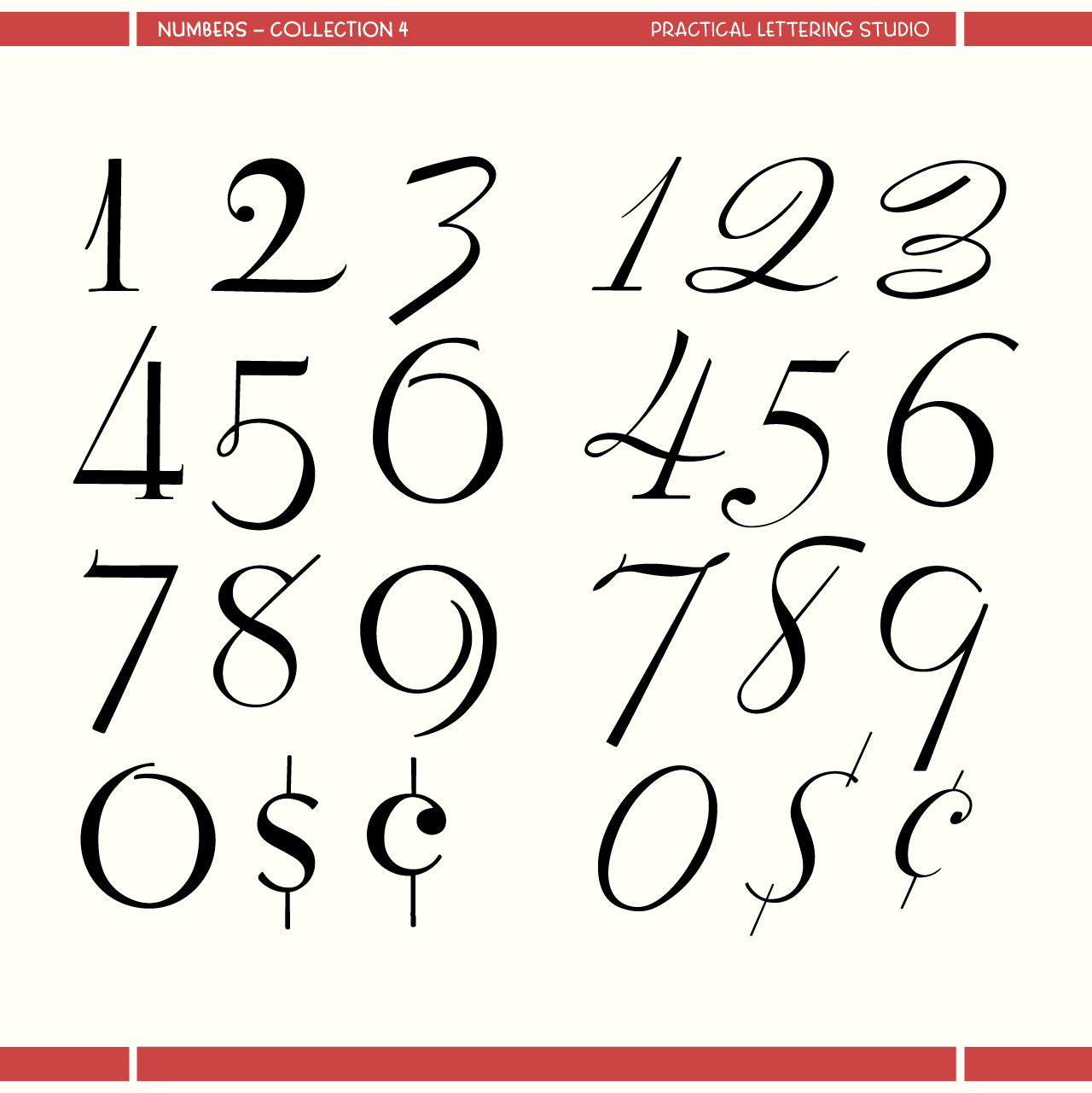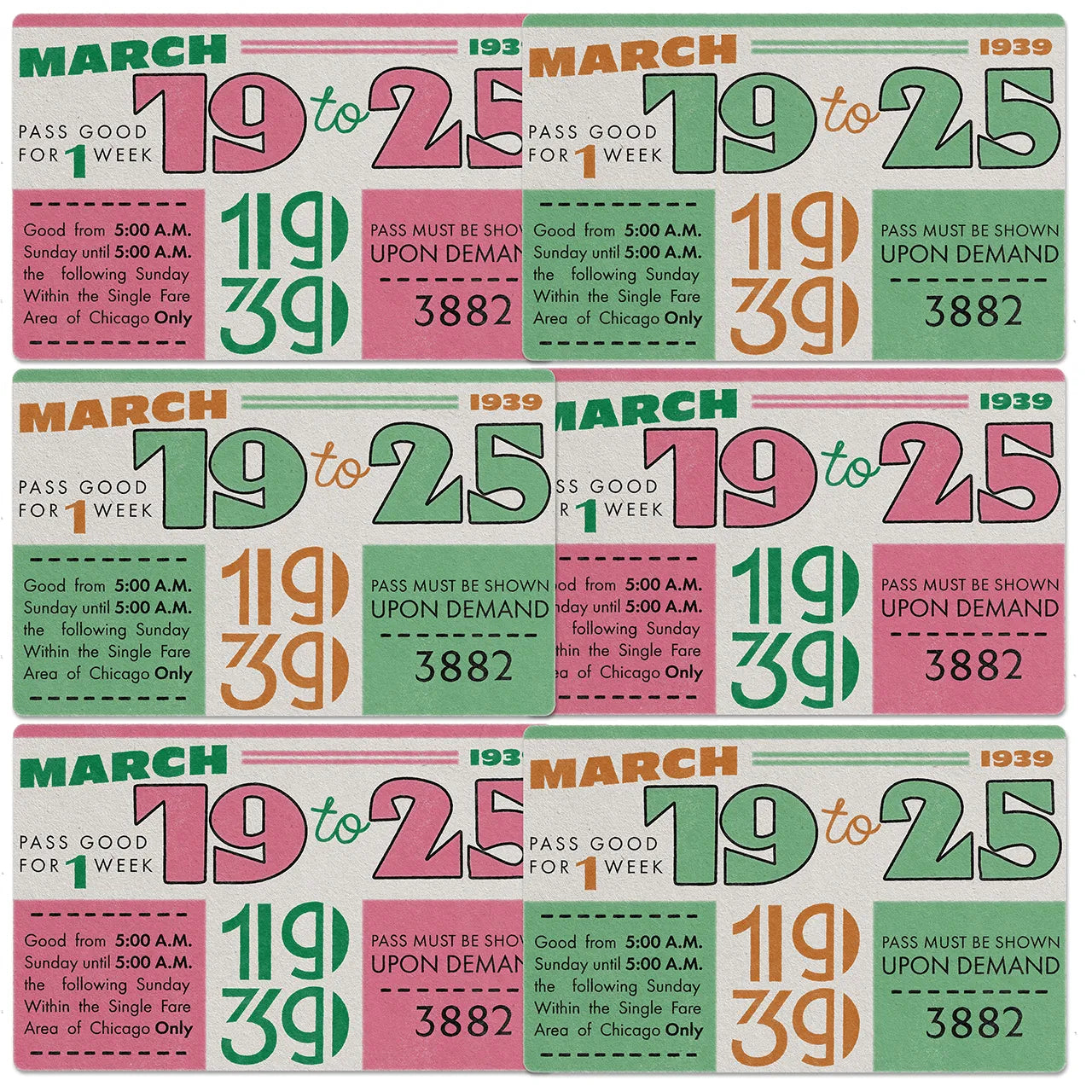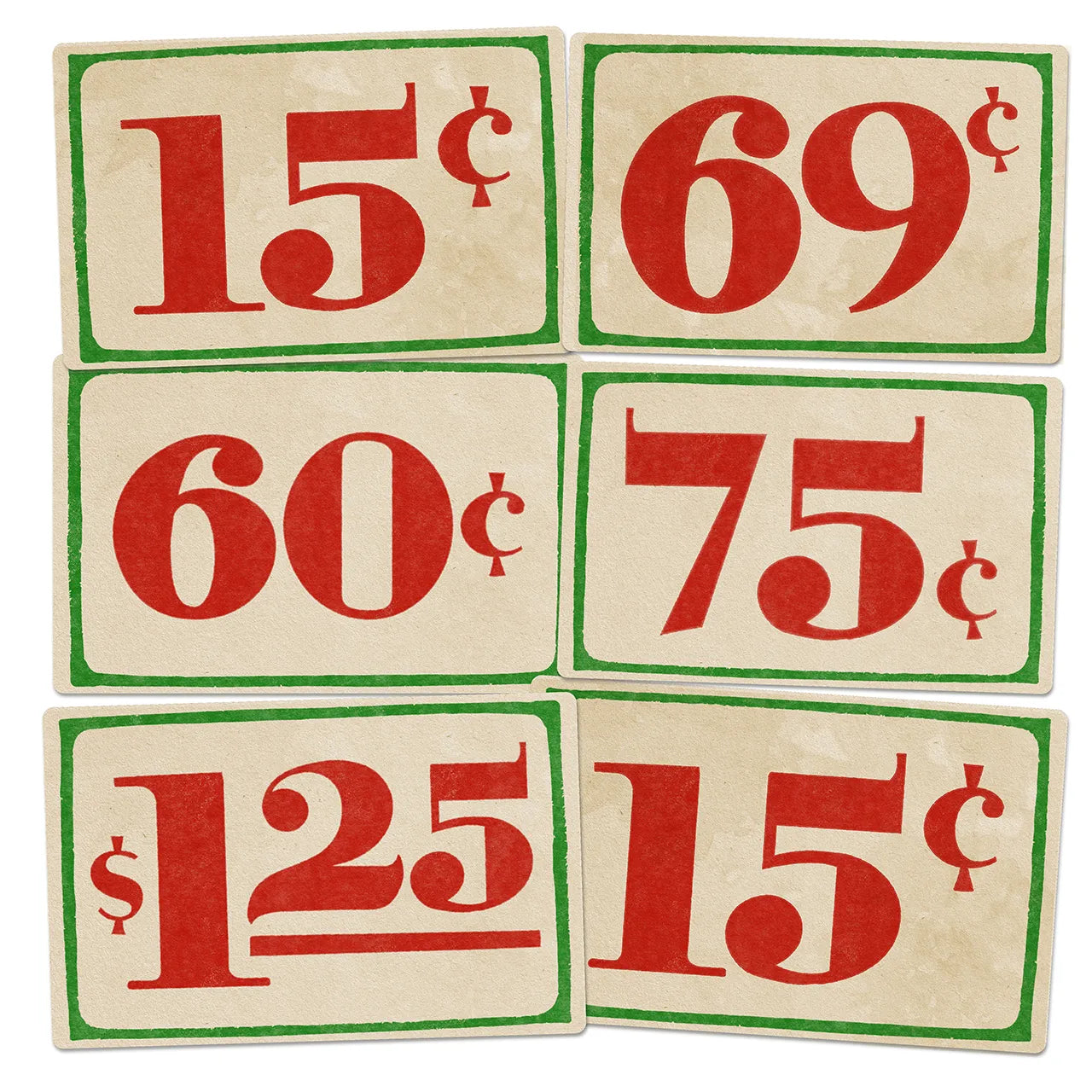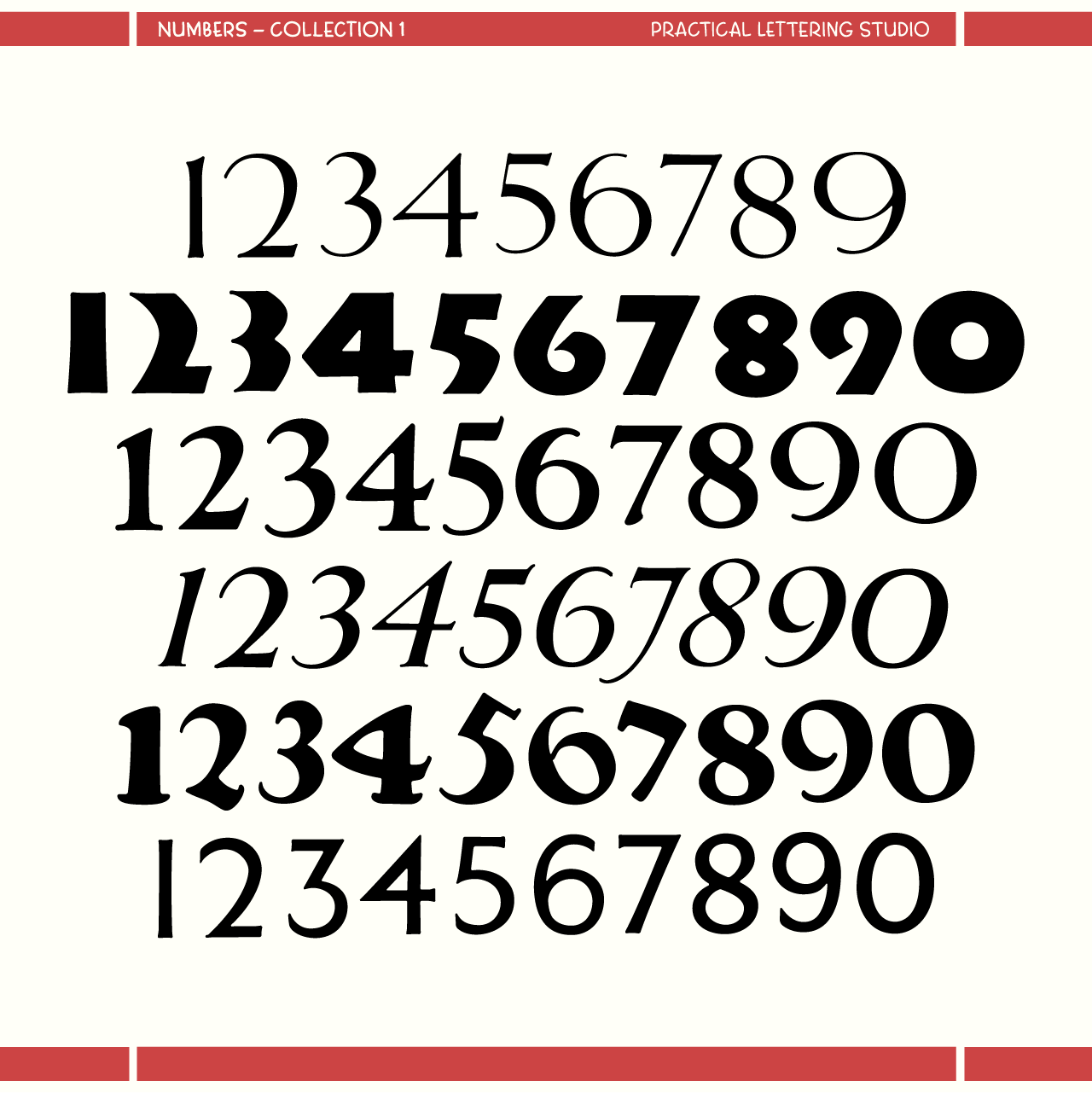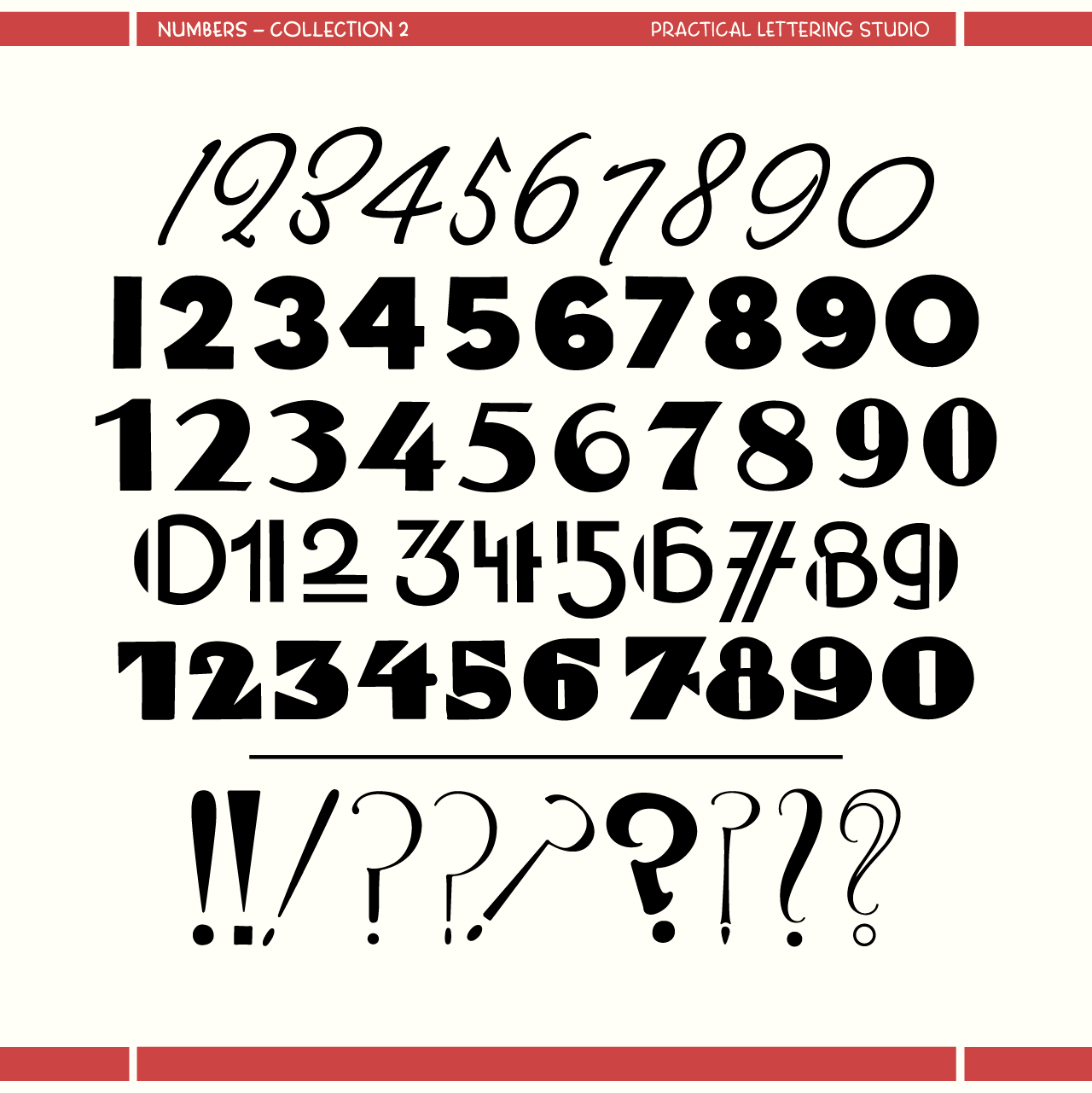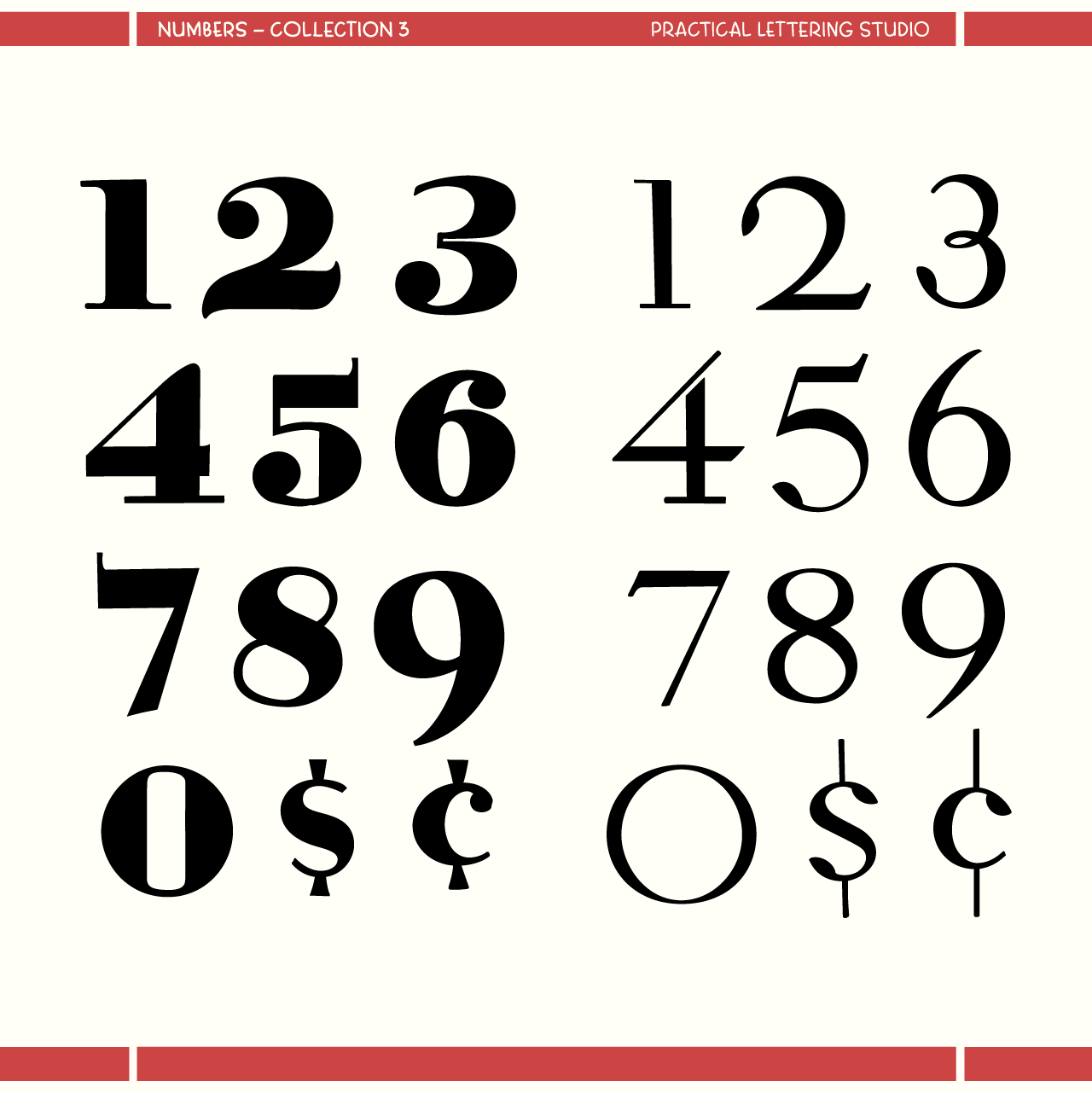
手書き数字
手書きの数字セット15種類が付属!
このベクターパックには、15種類の異なるヴィンテージスタイルの数字が含まれています。アールデコからそれ以降のミッドセンチュリースタイルまで、それぞれの数字セットは手書きで、値札、チケット、日付、そして注目を集める数字が必要なデザインのためにデザインされました。
スタイリッシュな疑問符のボーナスセットも含まれています...単に!
- 手書き数字のセットが15種類
- 1920年代から1950年代にかけての複数のスタイル